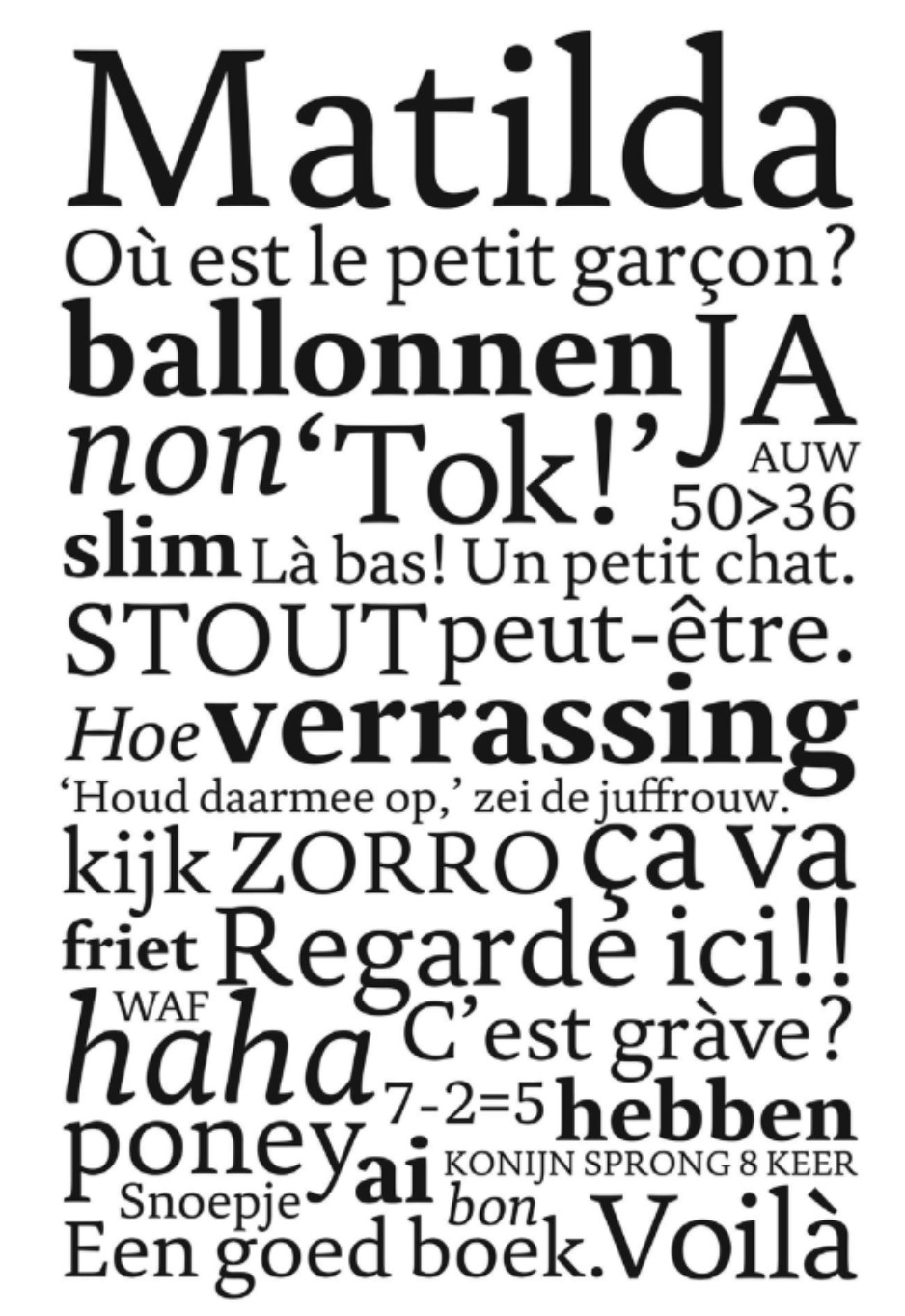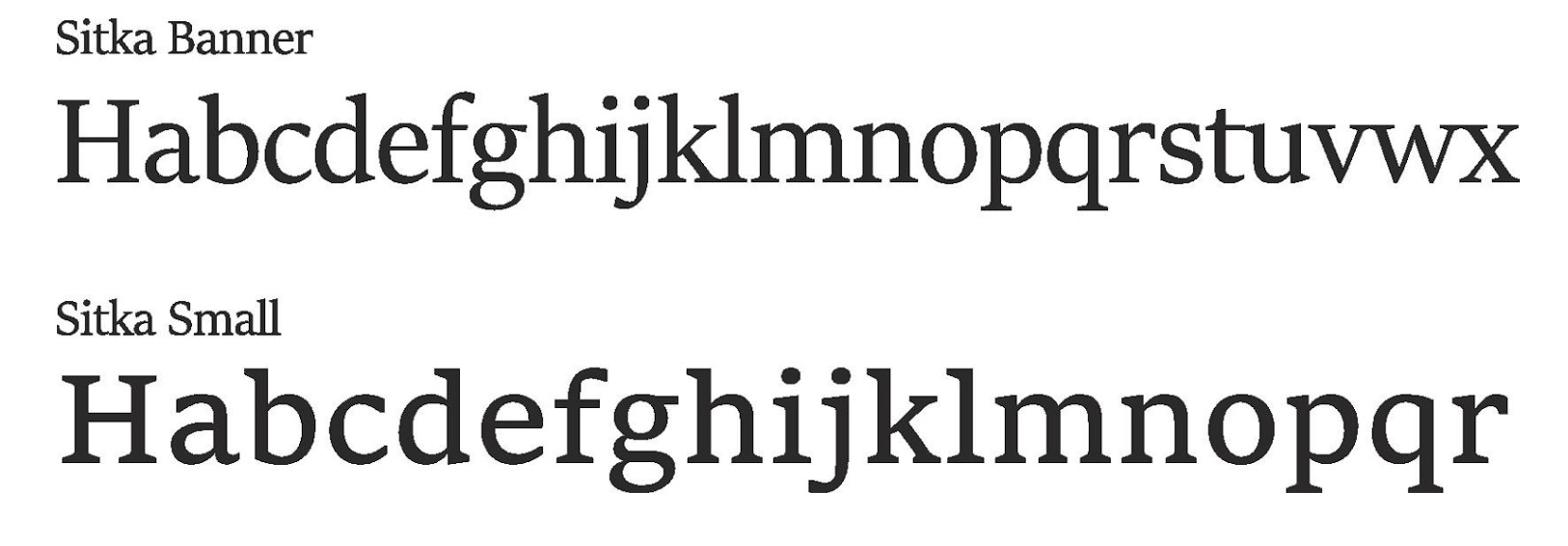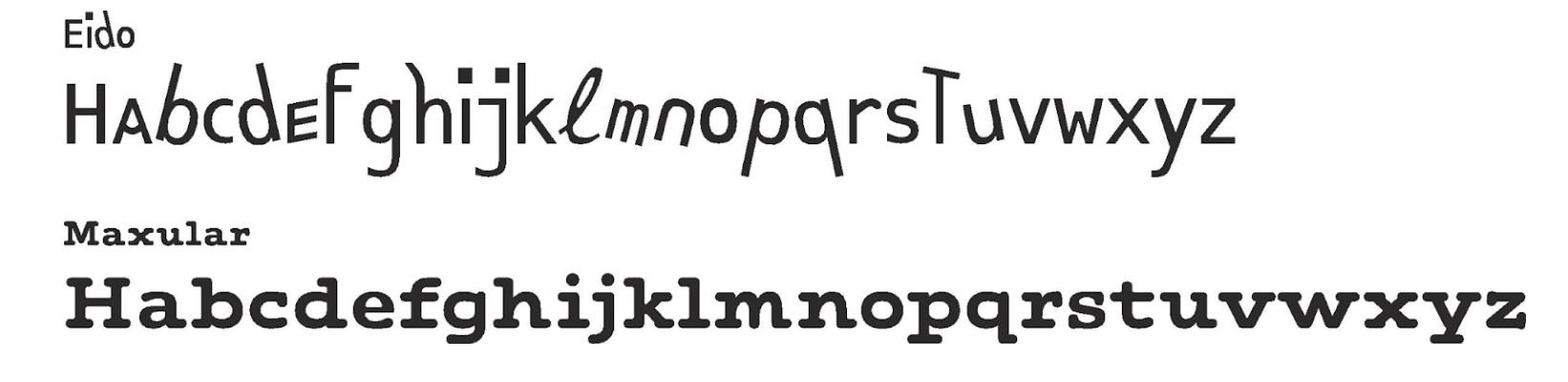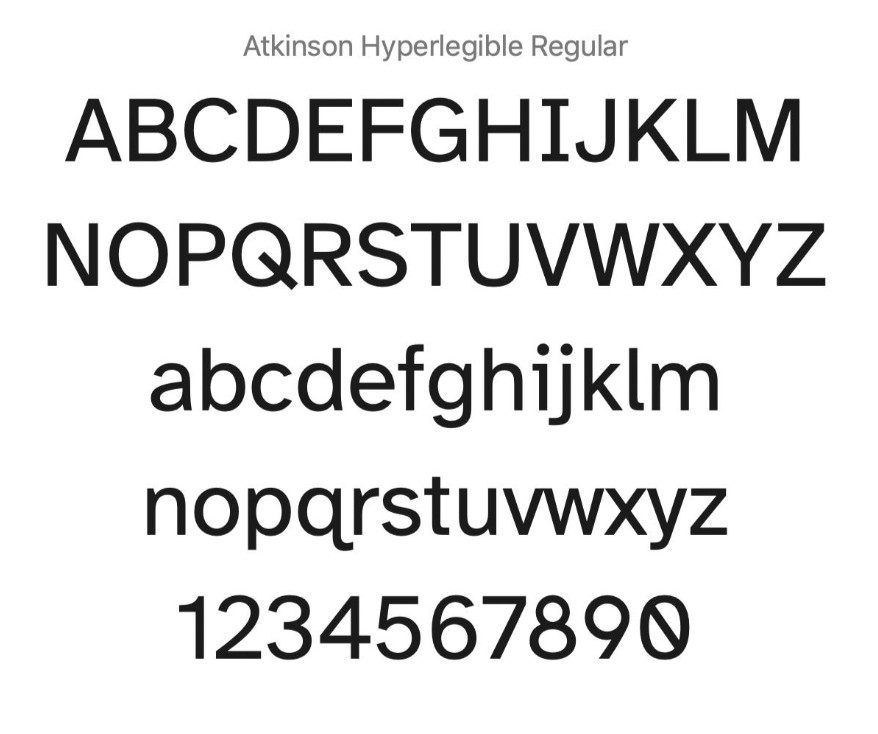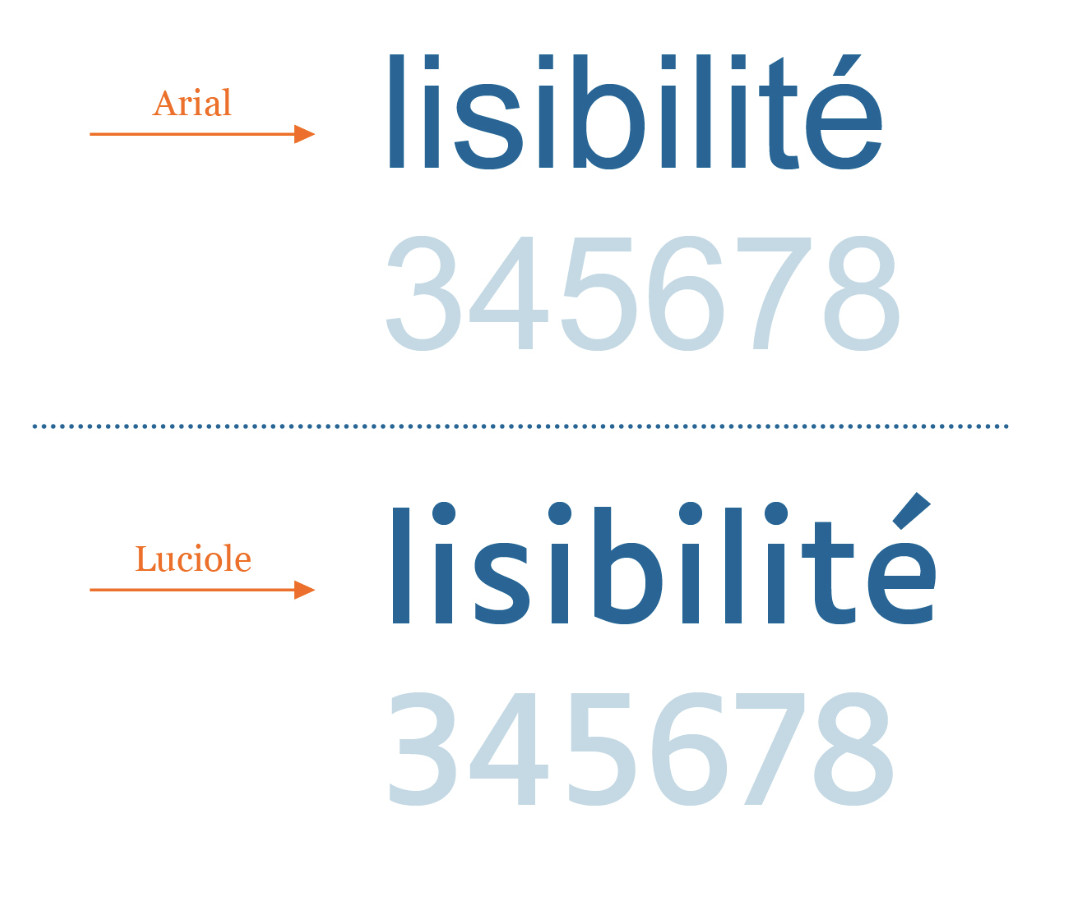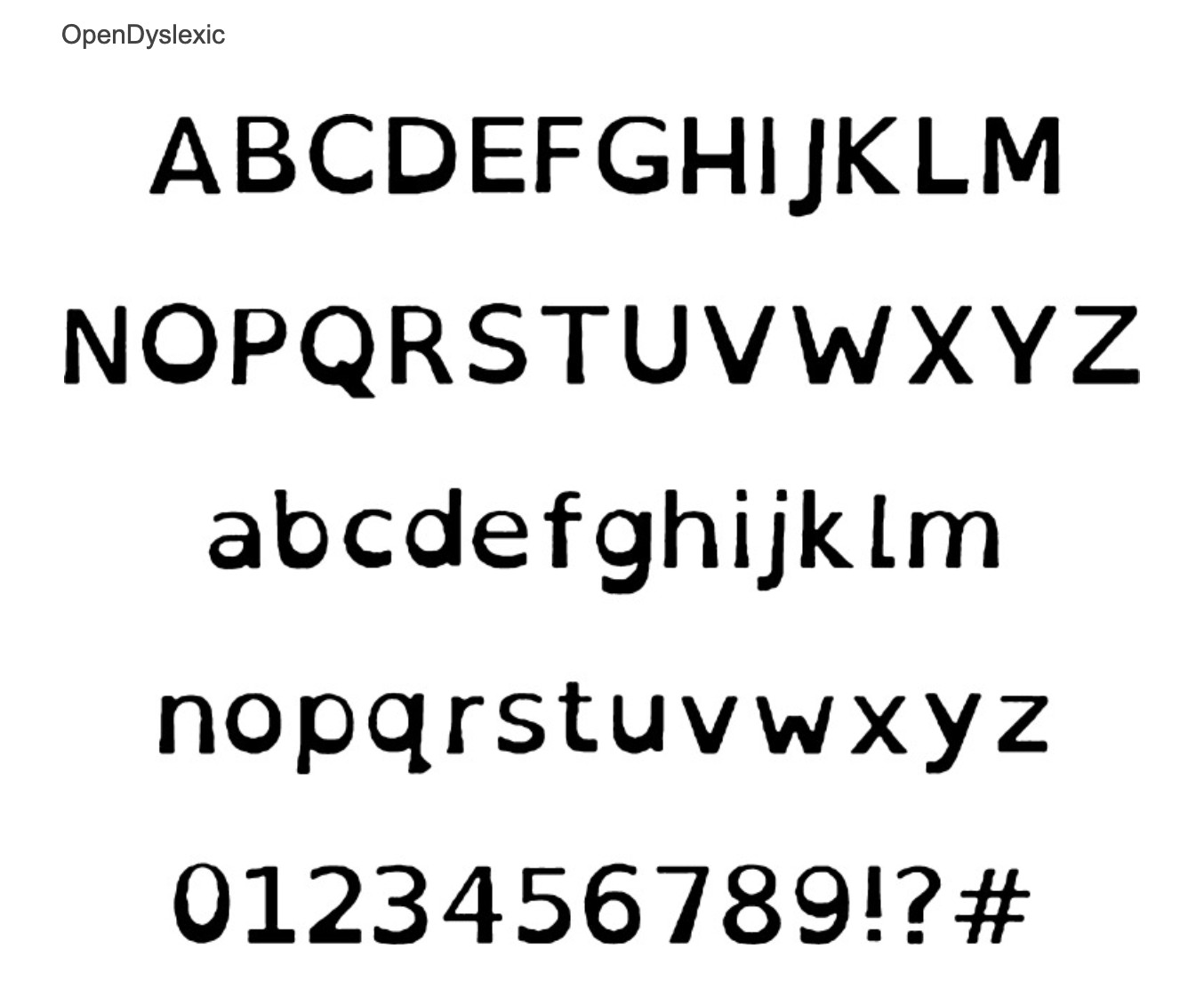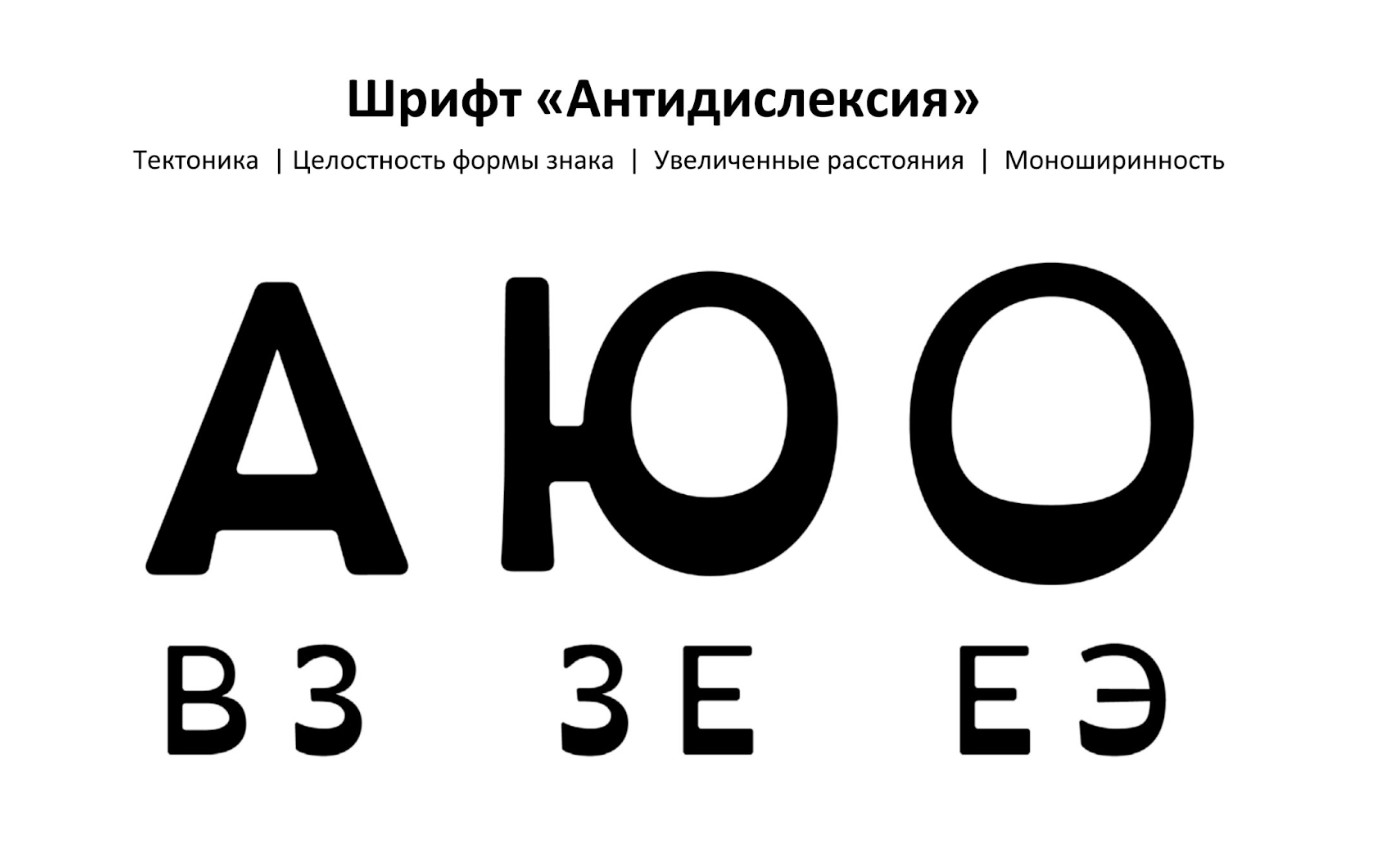
Шрифты, которые читают все: как цифровая доступность помогает вашему бизнесу
В мире, где внимание пользователя — самый ценный ресурс, нечитаемый шрифт может стать той невидимой стеной, о которую разбиваются ваши маркетинговые усилия, UX-дизайн и самые выгодные предложения. Ведь, по сути, шрифт — это фундамент вашего сайта, от которого зависит, насколько эффективно ваш контент достигнет цели.
И это не просто вопрос эстетики. Цифры говорят сами за себя: более миллиарда людей в мире живут с той или иной формой инвалидности. В России, по данным статистики, свыше 11 миллионов человек имеют официальный статус инвалида. И это лишь «верхушка айсберга», ведь временные ограничения, возрастные изменения зрения, дислексия и другие особенности восприятия текста затрагивают гораздо более широкую аудиторию — возможно, каждого третьего пользователя вашего сайта.
Игнорирование их потребностей — это не просто упущенная социальная ответственность, это — прямые финансовые потери. Исследования показывают, что сайты, недоступные для людей с ограниченными возможностями здоровья, ежегодно недополучают миллиарды рублей прибыли. Подробнее мы рассказывали в этой статье.
Проблема очевидна: большинство веб-ресурсов до сих пор не уделяют должного внимания цифровой доступности, в частности, используемым шрифтам. Дизайнеры часто руководствуются субъективными предпочтениями и трендами, забывая о главной цели шрифта — обеспечить максимально комфортное и эффективное чтение для всех пользователей. В результате, сайты теряют трафик, конверсию, лояльность клиентов и, в конечном итоге, прибыль.
Но выход есть! Многолетние научные исследования в области ассистивных шрифтов предоставляют четкую дорожную карту для создания сайтов, которые читают все и которые работают на ваш бизнес.
В этой статье мы раскроем научные секреты читаемых шрифтов, основываясь на обширном обзоре авторитетных исследований. Вы узнаете, какие шрифты действительно улучшают восприятие текста для разных групп пользователей, как избежать распространенных ошибок при выборе шрифтов и как персонализировать шрифт для максимальной доступности вашего сайта.
Готовы узнать, как сделать шрифт невидимым двигателем успеха вашего бизнеса?
Законодательство и этика: доступность шрифтов — это стандарт XXI века
Доступность шрифтов — это не просто «хороший тон» или тренд, это необходимость, продиктованная как законодательством, так и этическими нормами современного бизнеса.
Принцип воспринимаемого контента, закрепленный в международных стандартах веб-доступности (WCAG) и национальных стандартах, таких как ГОСТ Р 52872— 2019, гласит: информация и пользовательский интерфейс должны быть представлены пользователям так, чтобы они могли их воспринимать.
Этот фундаментальный принцип непосредственно относится и к выбору шрифтов. Хотя стандарты не диктуют конкретные шрифты, они недвусмысленно подчеркивают важность обеспечения доступности текстового контента для всех пользователей, включая людей с ограниченными возможностями здоровья. Более того, ГОСТ Р 59587-2021 устанавливает конкретные требования к шрифтовому оформлению текстов, предназначенных для чтения слабовидящими людьми, определяя параметры группы шрифтов, типа начертания, размера (кегля) и другие характеристики.
Таким образом, законодательство закрепляет важность доступности шрифтов как неотъемлемой части создания инклюзивного цифрового пространства. Игнорирование этих требований может повлечь за собой юридические последствия и репутационные риски для бизнеса.
Но доступность шрифтов — это не только вопрос соответствия нормам. Это, в первую очередь, вопрос этики и социальной ответственности. В XXI веке бизнес все больше осознает свою роль в создании равных возможностей для всех членов общества. Инклюзия становится ключевым принципом устойчивого развития и позитивного влияния на мир. Доступность шрифтов — это конкретное проявление этой этической позиции, забота о каждом пользователе, уважение к разнообразию человеческих потребностей.
И, наконец, доступность шрифтов — это разумная бизнес-стратегия. Создавая сайты, которые читают все, вы расширяете свою аудиторию, улучшаете пользовательский опыт, повышаете лояльность клиентов и, в конечном счете, увеличиваете свою прибыль.
В конкурентной борьбе за внимание пользователя, доступность шрифтов может стать тем решающим фактором, который выделит вас на фоне конкурентов и обеспечит вам долгосрочный успех. Доступность — это не обременение, а инвестиция в будущее вашего бизнеса.
Обзор научных исследований: карта знаний об ассистивных шрифтах
Интуиция и субъективный вкус — ненадежные советчики в вопросе выбора шрифтов для веб-сайта. Реальную основу для принятия обоснованных решений предоставляют научные исследования, посвященные изучению читаемости шрифтов для разных групп пользователей. Десятилетия исследований в этой области сформировали целую карту знаний об ассистивных шрифтах, позволяющую отделить зерна от плевел и выбрать решения, действительно работающие на практике.
Одним из самых масштабных и авторитетных трудов в этой области является обзор 18 научных исследований, опубликованный в Journal of Visual Impairment and Blindness. Этот фундаментальный анализ, охватывающий более 1500 испытуемых, позволяет обобщить ключевые тенденции и сделать data-driven выводы о наиболее читаемых шрифтах.
Ключевой вывод этого обзора, подтверждаемый и многими другими исследованиями, звучит однозначно: шрифты без засечек — лидеры читаемости на экране. Такие классические шрифты, как Arial, Helvetica, Verdana, Adsans, показывают наилучшие результаты в тестах на скорость и точность чтения, превосходя шрифты с засечками (serif) по большинству параметров. Именно шрифты без засечек рекомендованы в качестве основных для веб-контента в большинстве руководств по веб-доступности.
Особенно убедительно звучат результаты корейского исследования, которое количественно измерило влияние шрифта на скорость чтения для слабовидящих.
Эксперимент показал, что неправильный выбор шрифта может замедлить чтение для слабовидящих на целых 22.79%! Эта поразительная цифра наглядно демонстрирует, насколько критически важен шрифт для людей с ослабленным зрением и какой огромный барьер может создать неудачный шрифт.
В историю развития ассистивных шрифтов золотыми буквами вписаны имена Чарльза Бигелоу и Криса Холмса, разработавших в 80-х годах Lucida — одно из первых семейств шрифтов, созданных специально для экранов компьютеров и людей с нарушениями зрения.
Вслед за Lucida появился Tiresias PCfont, разработанный по заказу Королевского национального института слепых и также ориентированный на нужды слабовидящих. Эти шрифты стали пионерами в области ассистивных технологий и заложили основу для дальнейших исследований и разработок.
Интересным направлением стали эксперименты с параметрически настраиваемыми шрифтами, ярким примером которых является Font Tailor, разработанный Ардити в 2004 году.
Идея персонализации шрифта под индивидуальные потребности слабовидящих пользователей звучит весьма привлекательно. Однако, научные исследования не подтвердили значительного преимущества параметрически настроенных шрифтов перед более простыми и распространенными шрифтами, такими как Times New Roman. Этот пример подчеркивает важность научной проверки даже самых интуитивно верных идей и осторожность в отношении маркетинговых обещаний.
Особое внимание заслуживают исследования шрифтов, разработанных специально для детей с нарушениями зрения, ярким представителем которых является семейство Matilda Энн Бессеманс.
Бессеманс провела кропотливую работу, изучая влияние различных характеристик шрифтов на читаемость для школьников и разработала новые шрифты на основе полученных данных. Эти исследования вносят ценный вклад в понимание особенностей восприятия шрифтов детьми с нарушениями зрения и подчеркивают необходимость дифференцированного подхода к выбору шрифтов для разных возрастных групп.
Исследователи не обошли вниманием и оптически масштабируемые шрифты, такие как Sitka, разработанные Картером и Ларсоном в 2016 году.
Их удивительный вывод звучит парадоксально: корректировки для больших размеров шрифта не всегда улучшают читаемость крупного текста, а в некоторых случаях даже ухудшают ее! Исследования показали, что для крупных размеров часто более эффективным оказывается дизайн шрифта, изначально ориентированный на небольшой размер. Этот контринтуитивный результат заставляет задуматься о сложности механизмов зрительного восприятия и необходимости тщательного тестирования шрифтов для разных размеров и контекстов.
Шрифты Eido и Maxular Rx, специально разработанные для людей с дегенерацией желтого пятна, также стали объектом пристального внимания исследователей (Bernard, Aguilar & Castet, 2016, Стивен Скэггс). Сравнительные тесты с широко используемыми шрифтами, такими как Times New Roman, Helvetica и Courier, выявили нюансы в их эффективности и подчеркнули специфические требования к шрифтам для людей с данным заболеванием.
В современном ландшафте ассистивных шрифтов особое место занимает Atkinson Hyperlegible, разработанный в 2019 году студией графического дизайна Applied Design Works в сотрудничестве с Институтом Брайля.
Этот оптимизированный шрифт, созданный при участии слабовидящих людей, получил престижную награду Fast Company «Инновация в дизайне», что свидетельствует о его значительном влиянии на улучшение доступности. Atkinson Hyperlegible является ярким примером современного, data-driven подхода к разработке ассистивных шрифтов.
Шрифт Luciole, созданный междисциплинарной командой экспертов (офтальмолог, ортоптолог, психолог и типограф), также заслуживает внимания.
Исследования подтверждают его высокую эффективность по сравнению с рядом других ассистивных шрифтов, таких как Eido и OpenDyslexic, хотя в некоторых случаях он не превосходит классические шрифты без засечек, такие как Arial и Verdana.
Luciole демонстрирует важность комплексного подхода к разработке шрифтов, учитывающего не только типографские параметры, но и особенности зрительного восприятия и когнитивные факторы.
И, наконец, особо важно развеять миф о «волшебных дислексических шрифтах», таких как OpenDyslexic и Dyslexie. Несмотря на их широкую популярность и активный маркетинг, многочисленные научные исследования не подтверждают их значительного преимущества в читаемости для людей с дислексией перед обычными шрифтами.
Более того, некоторые исследования даже показывают отсутствие разницы или худшие результаты при использовании этих шрифтов. Хотя гипотеза об утяжелении нижней части букв звучит логично, научные данные не подтверждают ее эффективность и связывают позитивные результаты тестирования OpenDyslexic с особыми настройками интервалов.
Главный вывод исследований по дислексическим шрифтам звучит недвусмысленно: нет «волшебной таблетки», важнее комплексный подход к доступности, включающий выбор шрифтов без засечек, увеличение размера шрифта, межстрочного и межбуквенного интервалов.
Российские разработки Антидислексия и адаптивный шрифт ЦРПТ, хоть и являются интересным примером, но также, пока не имеют достаточного научного подтверждения своей эффективности.
Этот обзор исследований дает четкое понимание того, какие шрифты действительно работают, а какие являются лишь маркетинговыми мифами. Вместо поиска «волшебной таблетки», сосредоточьтесь на data-driven решениях, основанных на научных данных, и создавайте сайты, которые читают все и которые приносят реальную бизнес-выгоду.
Data-Driven рекомендации: шрифты, которые действительно улучшают читаемость
Основываясь на многолетних научных исследованиях и проведенном обзоре, мы можем сформулировать четкие и действенные рекомендации по выбору шрифтов, которые действительно улучшают читаемость и делают ваш сайт доступным для всех.
1. Выбирайте шрифты без засечек для основного текста — как подтверждают многочисленные исследования, включая обзор из Journal of Visual Impairment and Blindness. Шрифты типа Arial, Helvetica, Verdana, Adsans показывают наилучшую читаемость на экране и рекомендованы в качестве основных для веб-контента. Откажитесь от шрифтов с засечками (serif) для больших объемов текста — они ухудшают восприятие на экране и могут быть утомительными для читателя.
2. Увеличьте размер шрифта до не менее 16px для основного текста — это особенно важно для слабовидящих пользователей и подтверждено рекомендациями для слабовидящих, подкрепленными исследованиями. Не экономьте на пикселях — крупный шрифт — это визуальная щедрость для ваших пользователей, обеспечивающая комфортное чтение и снижающая утомляемость глаз. Для заголовков и подзаголовков используйте еще более крупные размеры шрифта, чтобы выделить структуру контента и облегчить навигацию по тексту.
3. Обеспечьте достаточный межстрочный и межбуквенный интервал — исследования показывают, что увеличение интервалов между строками и буквами улучшает читаемость и снижает утомляемость глаз. Не «лепите» строки и буквы друг к другу — дайте тексту «дышать», обеспечьте визуальное пространство, необходимое для комфортного восприятия.
4. Используйте контрастные цвета текста и фона — это базовый принцип веб-доступности, подтвержденный WCAG и многочисленными UX-исследованиями. Убедитесь, что соотношение контрастности соответствует стандартам доступности — не менее 4.5:1 для обычного текста и 3:1 для крупного текста. Контрастность — это «кислород» для читаемости, особенно для слабовидящих пользователей.
5. Избегайте курсива, узких начертаний и шрифтов, имитирующих рукописный текст — исследования показывают, что они ухудшают читаемость для всех групп пользователей, а особенно для людей с особенностями восприятия текста. Эти декоративные шрифты могут быть уместны для кратких выделений, но не для больших объемов основного текста.
6. Тестируйте разные шрифты и получайте обратную связь от пользователей — лучший способ убедиться в эффективности шрифта на вашей конкретной аудитории. Не полагайтесь только на общие рекомендации — проводите юзабилити-тестирование с участием реальных пользователей, собирайте их мнения и адаптируйте шрифты под нужды своей аудитории. Помните, что идеальный шрифт — субъективное понятие, и то, что работает для одной группы, может не подойти для другой.
Персонализация шрифта: дайте пользователям власть над текстом
Даже самые data-driven-оптимизированные рекомендации и лучшие шрифты — не панацея. Восприятие шрифта — субъективно, и то, что комфортно для одного пользователя, может быть неудобно для другого. Индивидуальные особенности зрения, когнитивные способности, личные предпочтения — все это влияет на восприятие текста. В этих условиях, наиболее эффективным решением становится предоставление пользователям власти над текстом, возможность самостоятельно настраивать отображение шрифта под свои индивидуальные нужды.
Именно персонализация шрифта является одной из ключевых функций виджета Assistapp. Наш инновационный инструмент позволяет пользователям мгновенно изменять отображение шрифта на более читаемый и комфортный именно для них шрифт.
Assistapp Widget предоставляет широкий спектр настроек, включая:
1. Выбор шрифта без засечек — основанного на научных исследованиях оптимального выбора для веб-контента. Пользователи могут легко переключиться на читаемый шрифт, обеспечивающий максимальную читаемость и универсальность.
2. Настройка размера шрифта — от мелкого до крупного, комфортного для любого зрения, особенно для слабовидящих пользователей. Больше не нужно напрягать глаза — пользователь может адаптировать отображение под индивидуальные потребности.
3. Регулировка контрастности и цветовые схемы — от классического черного на белом до инвертированных и альтернативных цветовых схем. Пользователи могут выбрать оптимальное сочетание цветов, снижающее утомляемость глаз и обеспечивающее максимальную различимость текста.
4. Включение специального «дислексического» шрифта — как дополнительная опция для пользователей, которые считают его более комфортным.
Виджет Assistapp — это не просто набор функций, это — философия уважения к пользователю, забота о его комфорте и возможность сделать ваш сайт по-настоящему инклюзивным.
Дайте своим пользователям власть над отображением вашего веб-сайта, откройте им мир комфортного веб-серфинга — и вы увидите, как возрастет их лояльность, удовлетворенность и время, проведенное на вашем сайте. Персонализация шрифта — это один из ключей к сердцам и умам ваших пользователей в XXI веке.
Шрифты, основанные на данных — ваш путь к доступному и успешному сайту
Выбор шрифтов для веб-сайта — это гораздо больше, чем дизайнерское решение. Это — стратегический выбор, влияющий на доступность, пользовательский опыт и бизнес-успех вашего ресурса. В мире, где каждая секунда внимания пользователя на счету, читаемость шрифта становится критически важным фактором удержания аудитории и достижения бизнес-целей.
Вместо интуиции и субъективных предпочтений, полагайтесь на научные данные. Многолетние исследования в области ассистивных шрифтов предоставляют четкие ориентиры для выбора действительно эффективных решений.
Выбирайте шрифты без засечек для основного текста, увеличьте размер шрифта до не менее 16px, обеспечьте достаточный межстрочный и межбуквенный интервал, используйте контрастные цвета текста и фона — эти data-driven рекомендации помогут вам создать сайты, которые читают все.
Развейте миф о «волшебных дислексических шрифтах» — научные исследования не подтверждают их значительного преимущества. Сосредоточьтесь на комплексном подходе к доступности и предоставьте пользователям власть над текстом.
Сделайте ваш сайт гостеприимным и удобным для каждого пользователя — и вы увидите, как возрастет ваша аудитория, лояльность клиентов и прибыль. Начните внедрять data-driven принципы выбора шрифтов уже сегодня: тестируйте разные варианты, персонализируйте шрифт с помощью Assistapp Widget, и откройте свой сайт для максимальной аудитории.
Создайте инклюзивный цифровой мир, где каждый имеет равные возможности получать информацию и взаимодействовать с вашим контентом. И пусть шрифт станет невидимым двигателем успеха вашего сайта.